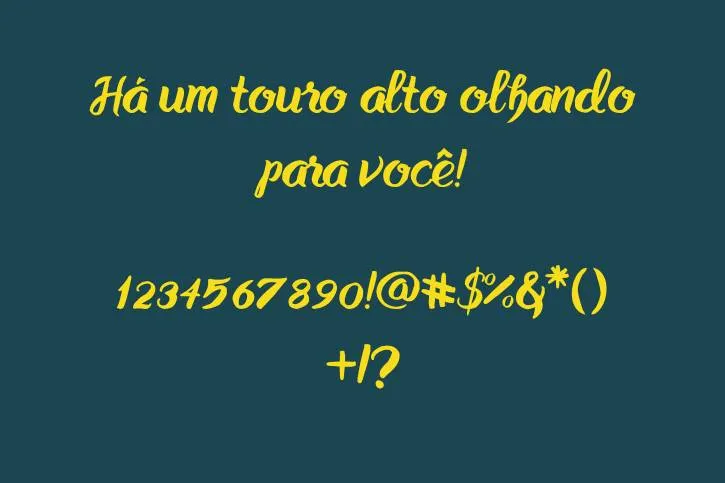
Fonte Olivia Garcia
A fonte Olivia Garcia é uma bela fonte Script, desenhada por Woodcutter e é conhecida por sua elegância e estilo sofisticado. Seus caracteres fluidos e conectados transmitem uma sensação de caligrafia, acrescentando um toque pessoal e artesanal ao texto. Suas linhas suaves e curvas elegantes criam um fluxo visual agradável.
Pode ser facilmente feito pelo designer combinando-o com a Fonte Lilly Belle, que é uma fonte semelhante. Uma característica marcante é a variedade de caracteres alternativos e traços, que permitem aos designers personalizar e decorar o texto de forma exclusiva. Isso proporciona grande flexibilidade no design, permitindo criar composições tipográficas únicas e expressivas.
Além disso, é altamente legível, mesmo em tamanhos menores, garantindo que o texto seja facilmente compreendido pelos leitores. Sua clareza e fluidez o tornam uma escolha versátil para uma variedade de aplicações de design gráfico. Outro aspecto atrativo é o seu aspecto natural e orgânico, que transmite uma sensação de autenticidade e personalidade.
Características da Fonte Olivia Garcia
É conhecido por sua elegância e estilo sofisticado, apresentando caracteres fluidos e conectados que transmitem uma sensação de caligrafia. Esse recurso adiciona um toque pessoal e artesanal ao texto, tornando-o uma escolha popular. Destaca-se também pelo seu aspecto natural e orgânico, transmitindo uma sensação de autenticidade e personalidade.
A fonte Bocadillo pode ser usada emparelhando-a com ela. Uma das principais características é a variedade de caracteres e traços alternativos. Isso permite que os designers personalizem e decorem o texto de forma única, oferecendo flexibilidade de design e possibilitando a criação de composições tipográficas únicas e expressivas.
Usando a Fonte Olivia Garcia em Designs
• Convites de casamento e artigos de papelaria para um toque elegante.
• Design de logotipo para adicionar um elemento pessoal e elegante.
• Embalagem de produto artesanal para um visual artesanal único.
• Gráficos de mídia social para transmitir uma vibração calorosa e amigável.
• Combine-a com a Hamburger para criar cabeçalhos e títulos de blogs para destacar o conteúdo.
• Cartões para uma mensagem personalizada e sincera.
• Cartazes artísticos e flyers para uma comunicação visual apelativa.
• Etiquetas de projetos artesanais e DIY para uma sensação caseira encantadora.
Imagem de Design da Fonte Olivia Garcia
Qual é a origem da fonte Olivia Garcia?
É uma bela fonte Script, desenhada por Woodcutter e é conhecida por sua elegância e estilo sofisticado.
O que faz a fonte Olivia Garcia se destacar?
Destaca-se pelo seu aspecto natural e orgânico, transmitindo uma sensação de autenticidade e personalidade.